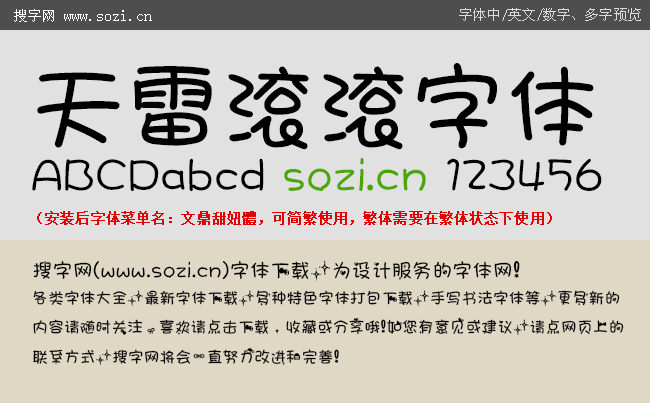
天雷滾滾字體
搜字網(wǎng)給大家提供一款很卡通的手機中文字體下載。修改者給這款字體叫天雷滾滾字體,這款手機中文字體以文鼎甜妞體為原形,將個別筆畫替換為卡通圖案,文鼎甜妞體的筆型渾厚圓潤,字構(gòu)活潑可愛,不同于一般傳統(tǒng)字型的刻版印象。具有青春活力、甜美可愛、自由、創(chuàng)新的特色。充滿孩童般童趣的天真氣息,在筆畫間嵌入卡通圖形,增加了趣味性,非常適合喜歡卡通的朋友在手機上安裝使用。